おしゃれなフリーフォントカタログ
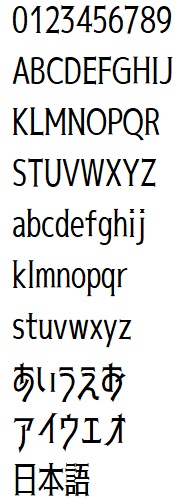
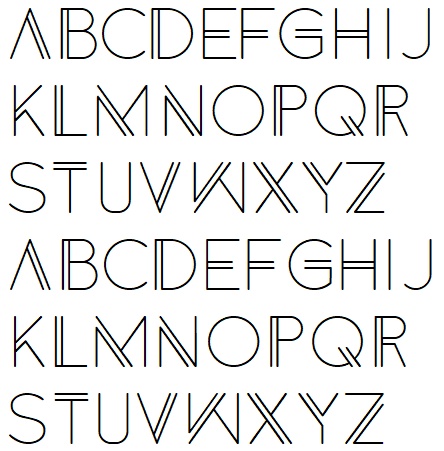
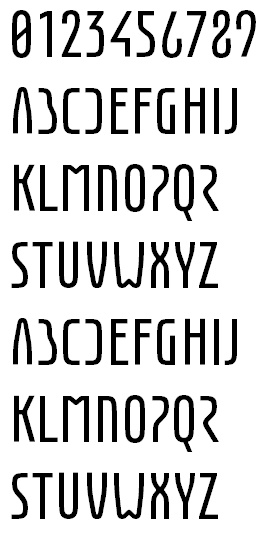
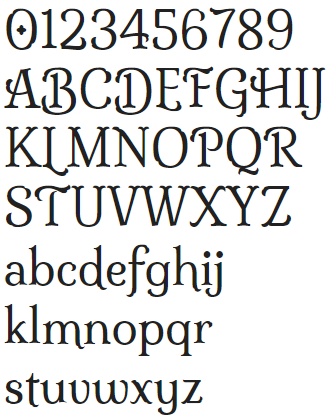
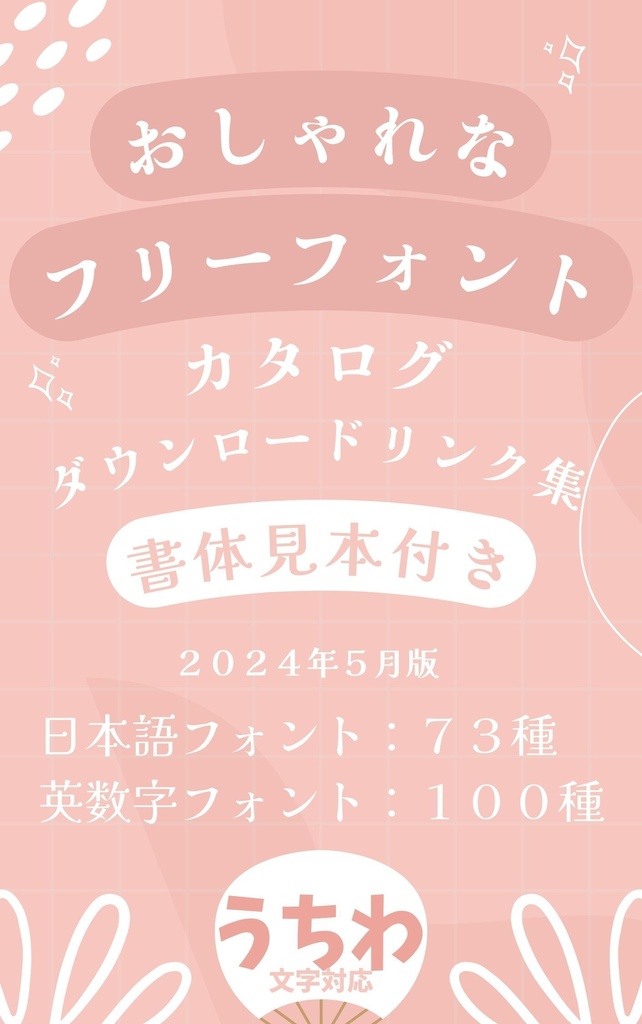
おしゃれなフリーフォントのガイド本です。 それぞれのダウンロードリンクと書体見本を収録しています。 ダウンロード前に書体見本で文字デザインを確認可能です。 おしゃれなデザインを作成したいかたにおススメです。 目次 日本語:明朝体 日本語:ゴシック体 日本語:丸ゴシック体 日本語:毛筆書体 日本語:手書き風書体 日本語:デザイン書体 英数字:クール 英数字:ディスプレイ 英数字:エレガント 英数字:手書き 英数字:レトロ 英数字:コミック 英数字:スポーツ 英数字:デザイン書体 ファイル形式:PDF (全272ページ) なお、フリーフォントは配布サイトが消えたり移動したりします。 そのようなフリーフォントを見つけた場合はお知らせいただけますと調査して更新します。 履歴: 2024.5 KindleからBOOTHへ変更